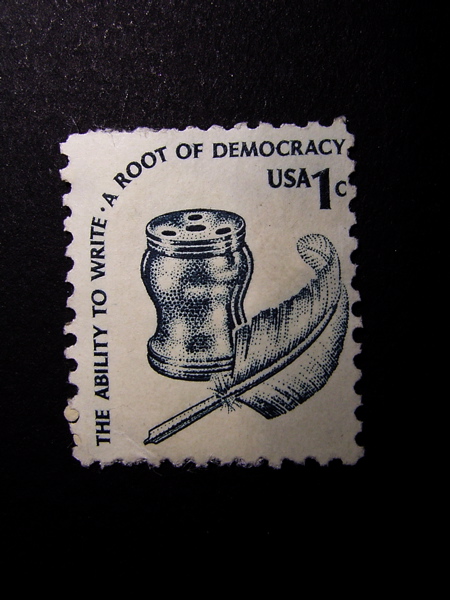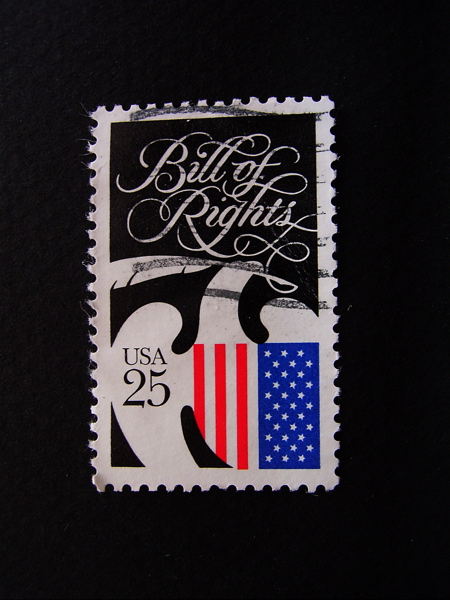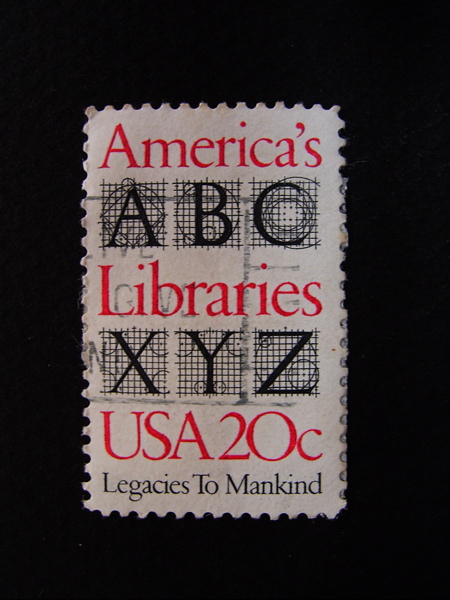
カリグラフィーの切手
文字好きの私たちにとっては、切手も大事なアイテムです。特に美しいアルファベットがデザインされた切手となれば、使用済みだろうとなんだろうととても貴重!
一つ目は美しいローマンキャピタルですが、ローマ時代のインスクリプション(碑文)からの形にしては、Cの上のカーブがやや下に下がっていて短いし、Zは幅がやや広すぎる感じがしますし、Aのクロスバーがやや上がっている様に思えます。それでも素敵なデザインですよね。
二つ目はJulian Watersのデザインした切手です。美しい文字のラインが羽根ペンにつながり、それを鳩がくわえています。黒地に白が本当に美しい。
三つ目は羽根ペンとインク壷?のデザインです。1セントの切手が文字を書く道具というところが嬉しいですねぇ!
切手はその小さな世界の中でデザインが完結していて奥が深く、見ていて飽きません。日本の切手は色の美しさでも有名ですが、残念ながらなかなかアルファベットは題材にはなりませんよねぇ、、、、(ひらがなや漢字のデザインは目にした事はありますけど。)
今日ご紹介したのはアメリカの切手ですが、いつかイギリスの切手もご紹介します。有名なカリグラファーのデザインしたクリスマスの切手は必見です。